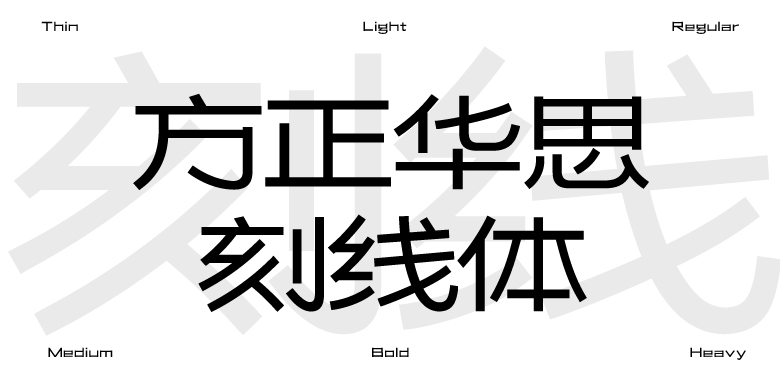
方正华思刻线体家族
这款字源于中学时代蜡纸刻印的心得而作,由于蜡纸油印文字容易印糊及文字不易识别,故在刻字时一笔一划,不连不断,不急不促,融入小篆的特征圆起圆收,方中寓圆,圆中有方,使转圆活,圆劲均匀富有奇趣;字体架构上横平竖直,平衡对称,上下左右空间均衡分割,行笔时化笔为刀,精简、朴实有力,斜笔直中微曲,气韵独特;为了解决油印的问题及印刷物的清晰阅读,故在刻字设计时中宫字面结构全部放宽,字面宽大使得整体字形清新易读,平稳端庄,和谐优美。本字稿为第十届方正奖入围作品。